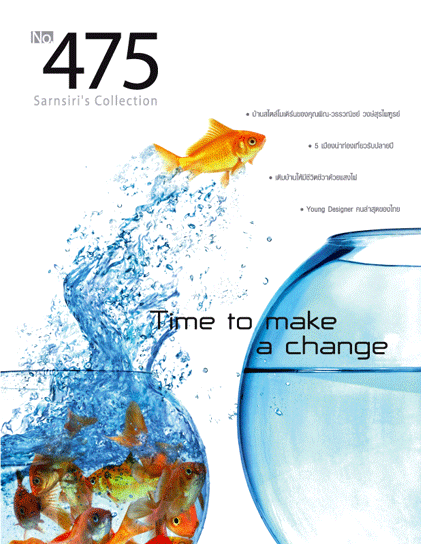
ลองเอาไปใส่ในงานแล้วลูกค้าชอบ เข้ากับ concept พอดี :12:
ไม่มีภาพเหรอครับ จะได้เอามาอวดกับ font คนอื่นมั่ง แบบนาน ๆ ทีมีคนใช้นะ  :35:
มีครับ...
เอาไปใช้เป็นตัวโปรยปก magazine น่ะครับ  :12: